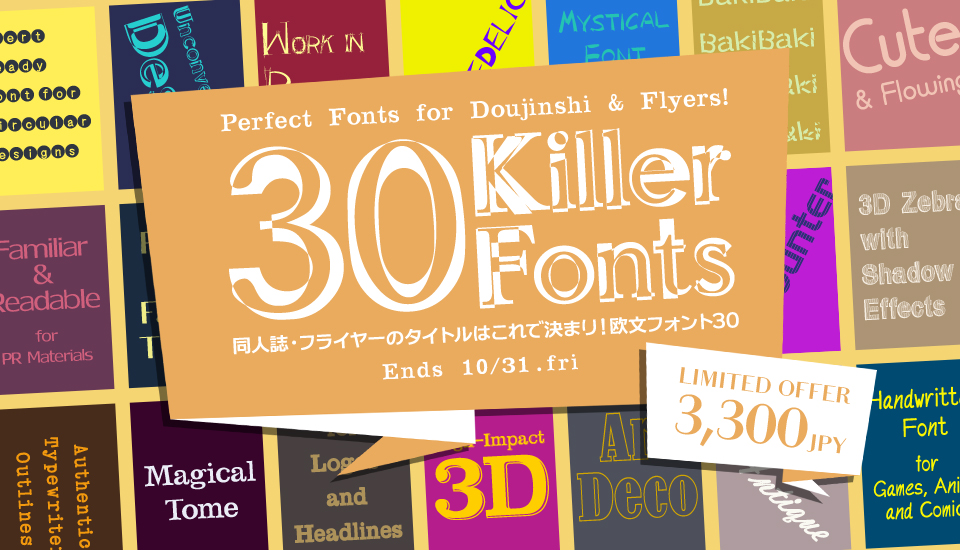
同人誌・フライヤーのタイトルで使える欧文フォント30書体セット
同人誌・フライヤーのタイトルはこれで決まり!欧文フォント30
FontUcom (フォントユーコム) の数あるラインナップの中から、同人誌やフライヤー・チラシを様々なテイストで表現できる欧文書体30書体を収録した特別セット30書体を収録。
同心円な欧文 Afconcentric、サークルな欧文 Afcircle、アンティークな筆記体 AFscriptAntiqueEB、アールデコ調な袋文字欧文 AFnouveauHollow、インデックス欧文 Afindex、タイプライター風本文用欧文 AFTypewriterEBP、ユーロスタイル欧文 AFNewEuroEB2、ゲームアニメ手紙用欧文 AFLetterB、PR専用欧文 AFStandardM、ミステリーな欧文 AFmysteryB、奇抜な欧文 Afoverlapped、製作途中イメージな欧文 AFBurr、トピック3Dゼブラかげ黒欧文 AFNewAriEB3Zebra3D、大見出し専用3D強カーニング欧文フォント AFDelFlorias3D、サイケデリックな欧文フォント Afpsychedelic、ミステリアスな欧文フォント AFTwilight、目立つ太めで細い欧文フォント AFTHICKTHIN、未来志向欧文 AFnewStyleB、ファッションサンセリフ欧文 AFFashionSansSerif、アメコミ古文書 欧文フォント AFWeddingText2、和食メニュー用 欧文フォント AFWasyokuP、魔導書表紙用欧文AFNecronomicon2、可愛い欧文フォント AFfunnyR2、極細欧文 AFHairLine2、AFWestern2 欧文、AFBakiBaki 欧文 4書体セット、AF-Necronomicon
1. 目立つ太めで細い欧文フォント AFTHICKTHIN
2. インデックス欧文 Afindex
3. 奇抜な欧文 Afoverlapped
4. 製作途中イメージな欧文 AFBurr
5. サイケデリックな欧文フォント Afpsychedelic
6. ミステリアスな欧文フォント AFTwilight
7. AFBakiBaki 欧文 4書体セット
8. 可愛い欧文フォント AFfunnyEB2
9. 未来志向欧文 AFnewStyleB
10. 極細欧文 AFHairLine2
11. PR専用欧文 AFStandardM
12. ファッションサンセリフ欧文 AFFashionSansSerif
13. ユーロスタイル欧文 AFNewEuroEB2
14. 本文用ナチュラルポップ欧文 AFnaturalPopB
15. チョーク欧文フォント AFChalk
16. 接近遭遇欧文 AFCloseEncounters
17. トピック3Dゼブラかげ黒欧文 AFNewAriEB3Zebra3D
18. 同心円な欧文 Afconcentric
19. ミステリーな欧文 AFmysteryB
20. タイプライター風本文用欧文 AFTypewriterEBP
21. 魔導書表紙用欧文 AFNecronomicon2
22. 大文字専用欧文フォント AFDelFloriasEB
23. 大見出し専用3D強カーニング欧文フォント AFDelFlorias3D
24. アールデコ調な袋文字欧文 AFnouveauHollow
25. アンティークな筆記体 AFscriptAntiqueEB
26. ゲームアニメ手紙用欧文 AFLetterB
27. 和食メニュー用 欧文フォント AFWasyokuP
1. 目立つ太めで細い欧文フォント AFTHICKTHIN
同人誌・フライヤーのタイトルはこれで決まり!欧文フォント30 目立つ太めで細い欧文フォント AFTHICKTHIN イメージ
目立つ太めで細い欧文フォント AFTHICKTHIN
極端に太い縦線と極端に細い中心横線。大見出し、大きく表現したい場所、インパクトを与えたいメッセージに最適な大文字用欧文フォントです。
2. インデックス欧文 Afindex
同人誌・フライヤーのタイトルはこれで決まり!欧文フォント30 インデックス欧文 Afindex イメージ
インデックス欧文 Afindex
円の中に丸ゴシック系の欧文を入れたフォントです。箇条書きなど段落や注意喚起など強いメッセージ用としてお使い頂けます。
3. 奇抜な欧文 Afoverlapped
同人誌・フライヤーのタイトルはこれで決まり!欧文フォント30 奇抜な欧文 Afoverlapped イメージ
奇抜な欧文 Afoverlapped
とにかく目立つ、サイケデリックな表現に最適な字形デザイン。奇抜でもカーニングもしっかりセット、個人同人向けアニメ、動画向けなフォント。
4. 製作途中イメージな欧文 AFBurr
同人誌・フライヤーのタイトルはこれで決まり!欧文フォント30 製作途中イメージな欧文 AFBurr イメージ
製作途中イメージな欧文 AFBurr
ガイド風な直線から曲線を描き欧文フォントを作成する手順でデザインされた文字。さらにガイド直線をあえて残すことで、何らかの作業中だったり開発途中であるかのイメージを保ちます。提案・企画・設計などドキュメントにおける表紙に。
5. サイケデリックな欧文フォント Afpsychedelic
同人誌・フライヤーのタイトルはこれで決まり!欧文フォント30 サイケデリックな欧文フォント Afpsychedelic イメージ
サイケデリックな欧文フォント Afpsychedelic
虚構でファンタジーな世界を極彩色で演出するための欧文フォントです。
6. ミステリアスな欧文フォント AFTwilight
同人誌・フライヤーのタイトルはこれで決まり!欧文フォント30 ミステリアスな欧文フォント AFTwilight イメージ
ミステリアスな欧文フォント AFTwilight
ミステリアスや禍々しさ、暗黒等を想像させる場面、虚構な表現にお使い頂けるスモールキャップな欧文フォントです。
7. AFBakiBaki 欧文 4書体セット
同人誌・フライヤーのタイトルはこれで決まり!欧文フォント30 AFBakiBaki 欧文 4書体セット イメージ
AFBakiBaki 欧文 4書体セット
バキバキに折れた印象を与える欧文フォント。折れ方のバリエーションをGIF化することで文字にストーリーを与える事ができます。
8. 可愛い欧文フォント AFfunnyEB2
同人誌・フライヤーのタイトルはこれで決まり!欧文フォント30 可愛い欧文フォント AFfunnyEB2 イメージ
可愛い欧文フォント AFfunnyEB2
大文字と小文字のアセントを近づけ流れる読みやすさを実現。強めのカーニングがリーフレットやお洒落なドキュメントに最適です。
9. 未来志向欧文 AFnewStyleB
同人誌・フライヤーのタイトルはこれで決まり!欧文フォント30 未来志向欧文 AFnewStyleB イメージ
未来志向欧文 AFnewStyleB
曲線を多用強調したSF感ある未来志向な欧文フォントです。スタイリッシュな場面や注目を得たいキーワード、ドキュメントに最適です。日本の住所を欧文表記する場合の訓令式やヘボン式で扱う Ô や Ō の文字も収録しました。
10. 極細欧文 AFHairLine2
同人誌・フライヤーのタイトルはこれで決まり!欧文フォント30 極細欧文 AFHairLine2 イメージ